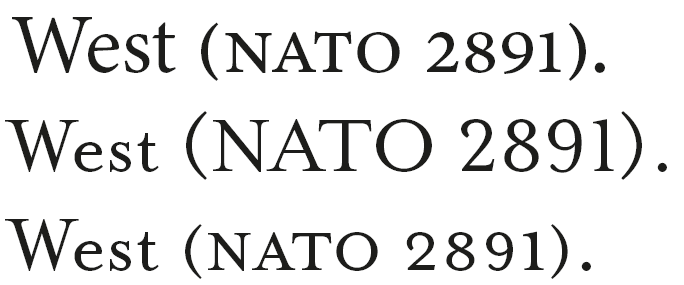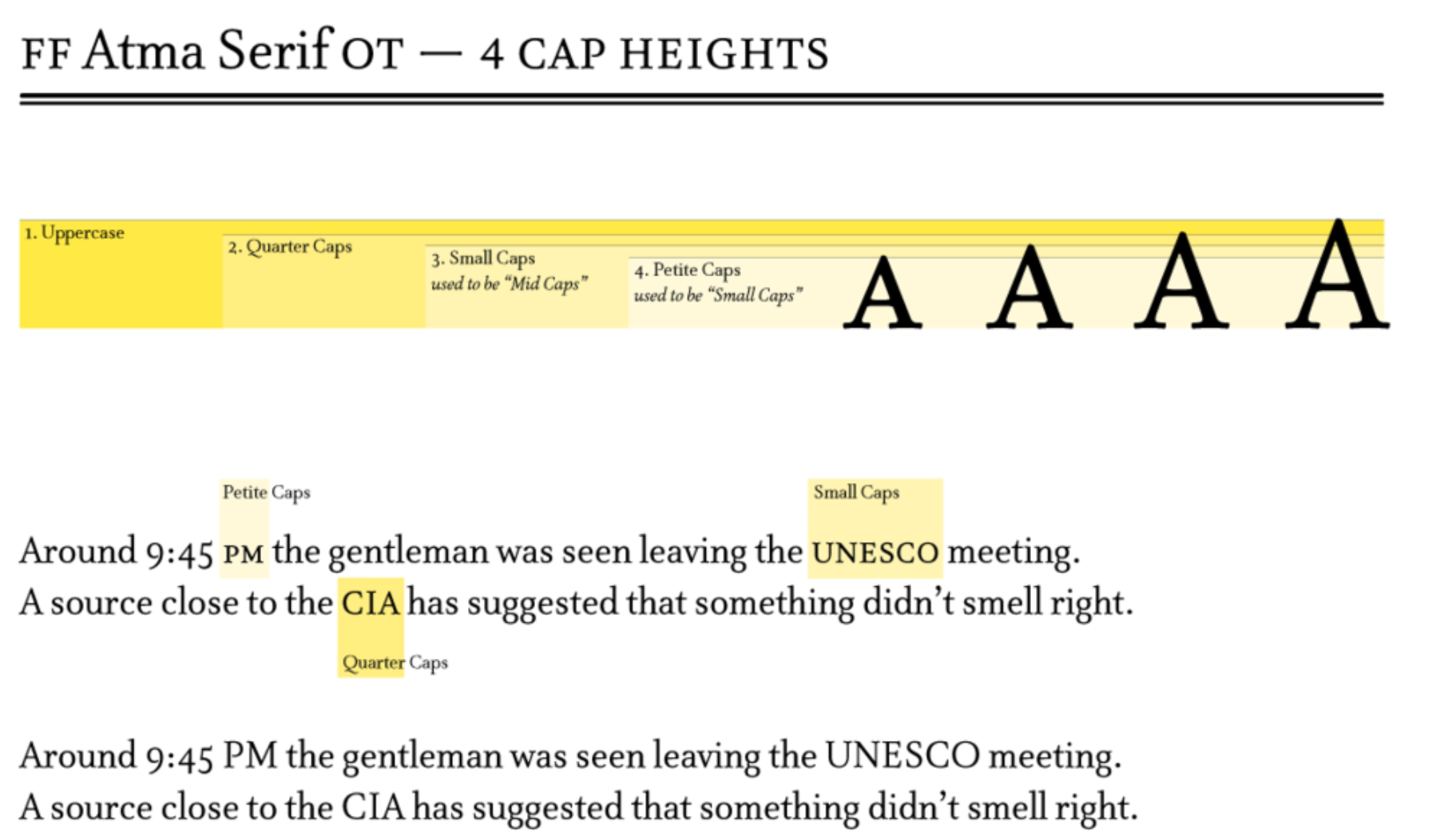
Schriften mit mehreren "Caps/Smallcaps"-Varianten gesucht
Ich suche Schriften, die verschiedene »Größen« für Versalien und Kapitälchen haben. Also z. B. wie bei der FF Atma:
Oder Mrs Eaves, etc.
dumme frage meinerseits: warum möchtest du so eine schrift? gibt es innerhalb eines projektes anwendungsmöglichkeiten für mehrere verschiedene sinnvolle small caps varianten?
@Carlito Palm: Ja, die Anwendung gibt es. Acronyme wie im oben dargestellten Beispiel sehen meiner Ansicht nach besser aus, wenn sie eine Größe zwischen Versalien und Kapitälchen (= etwas über x-Achse, Minuskelhöhe) haben. Auszeichnungen in Versalien, was manchmal vom Kunden »erzwungen« wird, wirken meist zu schreiend und fallen aus dem Satzbild zu sehr heraus. Früher hat man sich damit beholfen, diese um einen Punkt kleiner zu setzen. Das hat wiederum das Problem, dass die Versalien dann zu »dünn« gegenüber den daneben stehenden Großbuchstaben wirken. Eine Schrift die wie oben gezeigt »Mid Caps« oder »Quarter Caps« anbietet, löst dieses Problem wunderbar.
Ein weiteres Problem in diesem Zusammenhang sind Kombinationen solcher Wörter mit Klammern und Ziffern, die zu diesen Größenvarianten passen sollten.
wenn ich das richtig verstehe: für abkürzungen etc. sind dir die small caps zu klein (bzw bei »versalsatz« dem kunden). ich verwende da immer die kapitälchen weil die sich schön in den fließtext einfügen.
Ich kenne das Problem aus der Praxis ...
Die Smallcaps sind gut als Auszeichnung normaler Worte (wie eine Kursive), also wenn ich was formal markieren will, es aber nicht unbedingt hervorstechen soll.
Aber wenn ich eine Abkürzung habe, die eigentlich die versalen Anfangsbuchstaben einer Langbezeichnung enthält, dann wird das in Kapitälchen innerhalb des Textes oft "zu klein", besonders kurze Abkürzungen (UN) gehen dann oft ganz unter und werden nicht mal mehr als Abkürzung wahrgenommen.
Die Versalien selbst sind hingegen (in manchen / vielen Schriftarten) wieder zu groß und wirken bei langen Abkürzungen (UNESCO) wie eine aktive Auszeichnung – die sollen ja im Text auch nicht herausstechen.
Kurze und lange Abkürzungen unterschiedlich handhaben ist schwierig, es gibt dann immer Grenzfälle und die Diskussion mit dem Auftrageber ist bei sowas schwierig.
Ein Mittelding ist da sehr willkommen ... leider so selten, dass man es natürlich nie in der jeweiligen CI-Schrift vorfindet, wenn man es mal braucht ...
Die FF Ernestine Pro hat zwei Größen an Kapitälchen. Die eine normal erreichbar, die andere über einen Formatsatz.